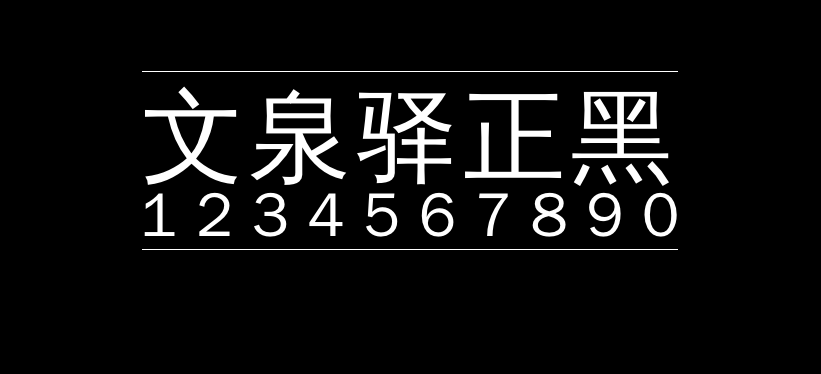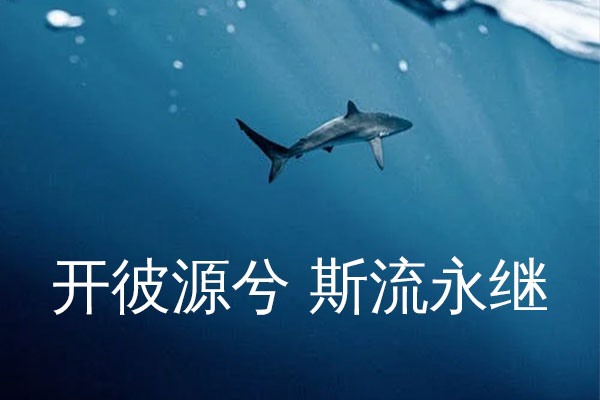
文泉驿正黑
文泉驿正黑体来自学者房骞骞2004年发起的公益项目——文泉驿;文泉驿正黑体是一个”自由字体”。该字体包含了所有常用简体中文、繁体中文所需要的汉字(最新版本包含超过27842个汉字,完整覆盖GB2312/Big5/GBK以及GB18030标准字符集)。该字体同时还包含了日文、韩文和其他几十种语言符号。除此以外,该字体还嵌入了最新版本的文泉驿点阵宋体的中英文点阵,使得屏幕汉字显示清晰锐利,易于阅读。
作为黑体中文字体,文泉驿正黑为非衬线字体,笔画对比度明显,特别适合屏幕汉字显示以及文档标题字体。
说到中文字体开源的鼻祖,学者房骞骞2004年发起的公益项目文泉驿应该算一个,开源、允许商业发布。据说发起这个项目,初衷是改善当时高质量中文字体匮乏的情形,以适应Linux系统开发。字体不多,但支持的字很全。可惜很早之前已经停止更新,也没有更多新的免费字体。确实要维护公益性项目实在是困难重重。